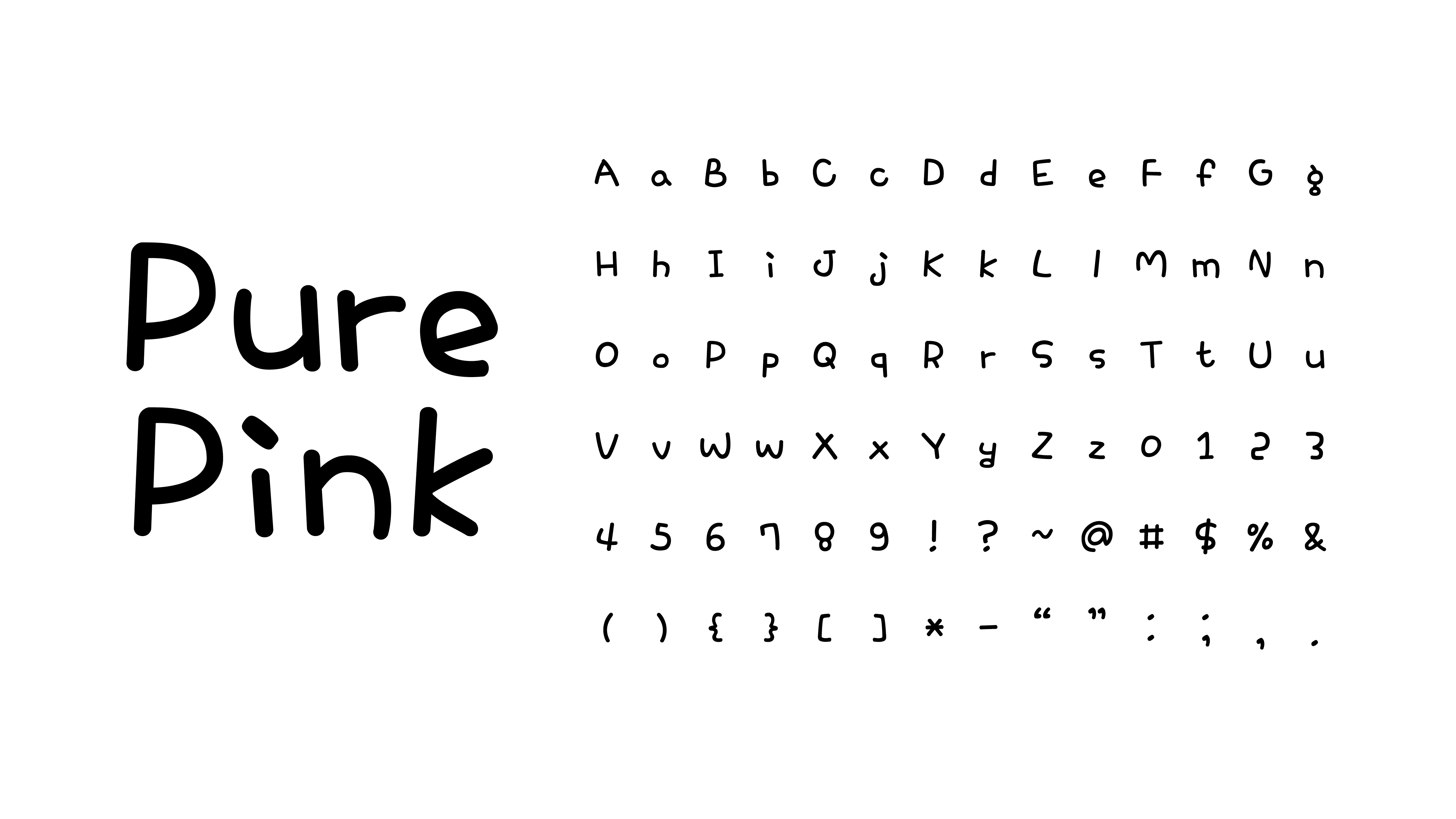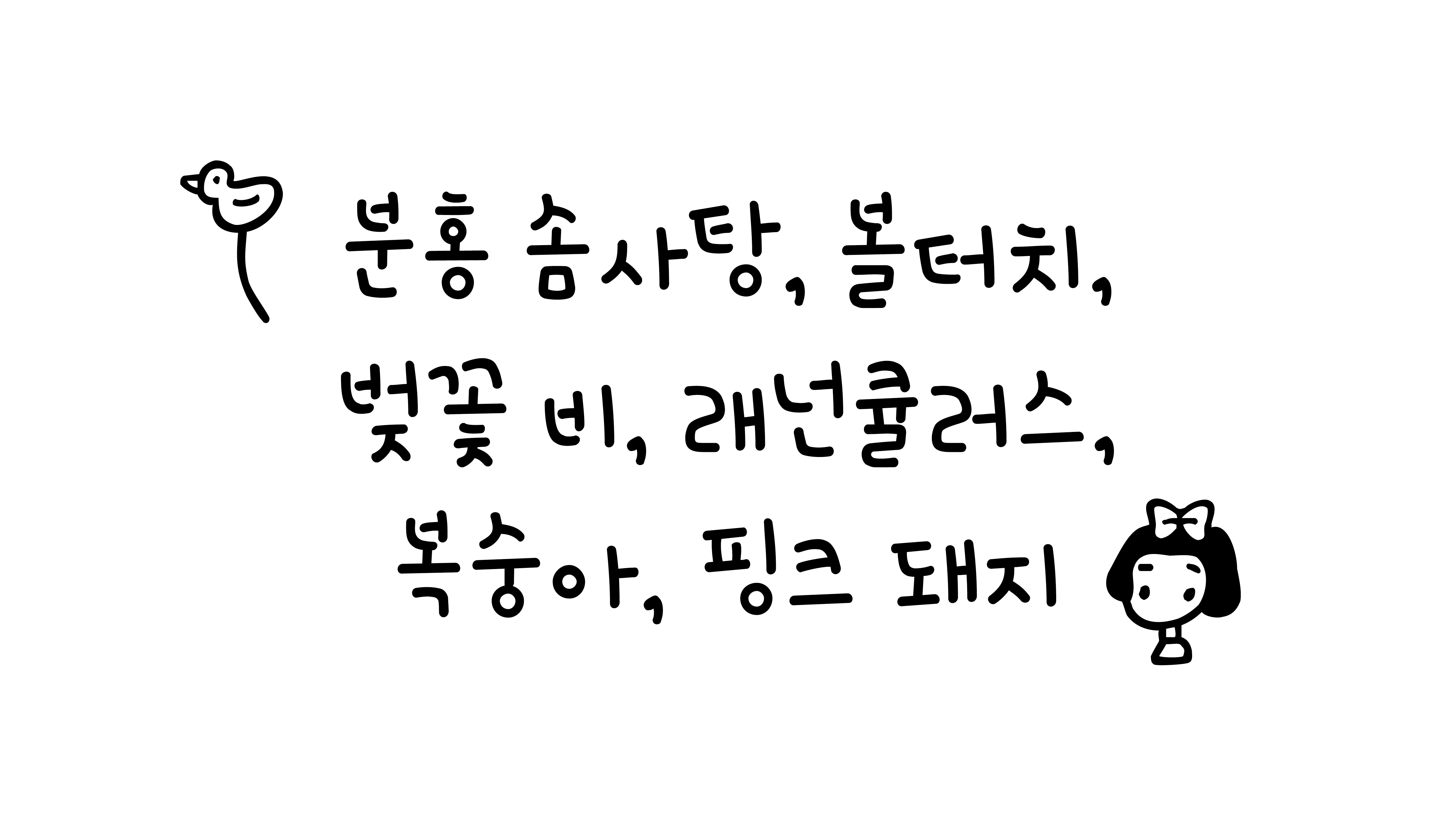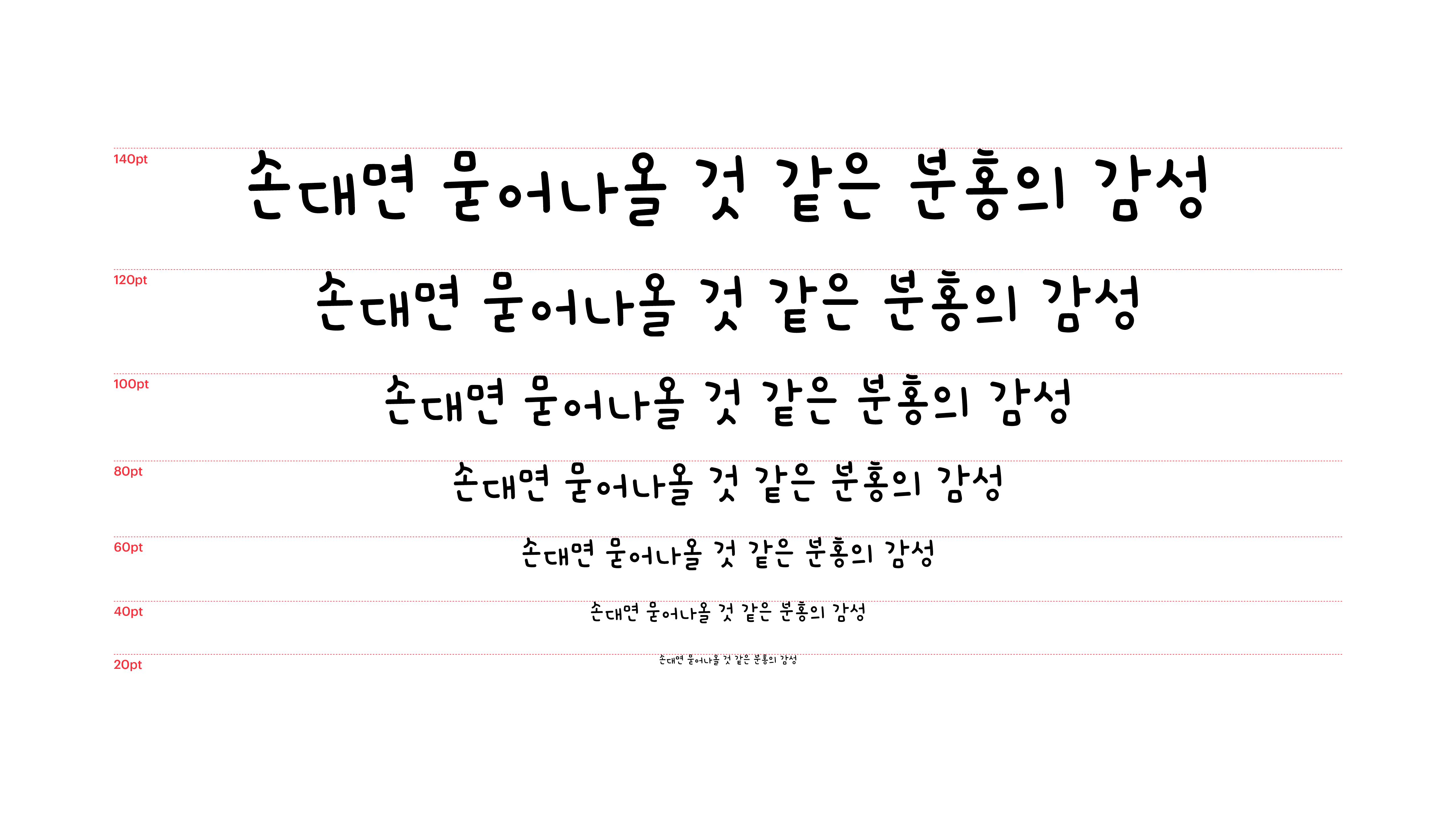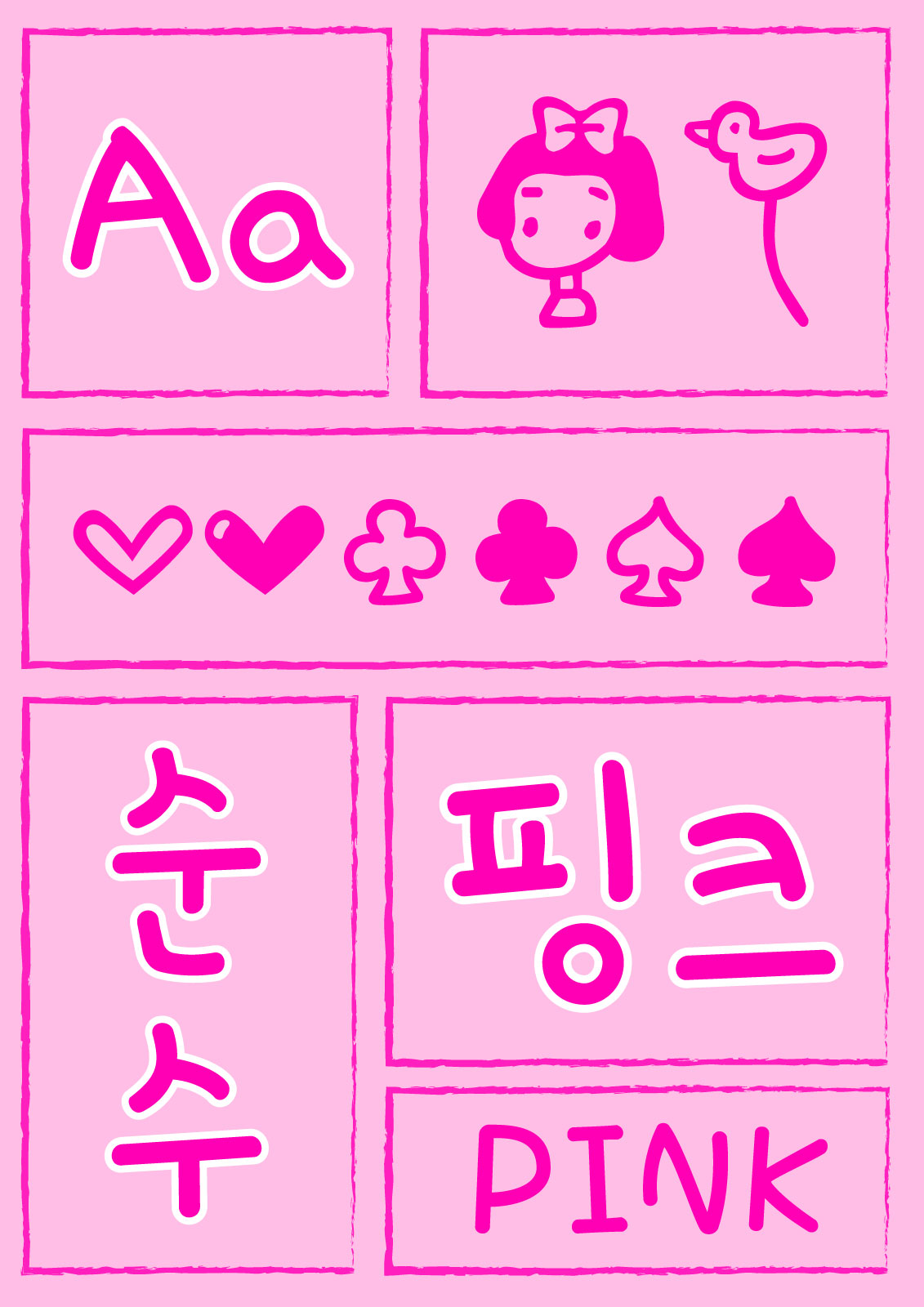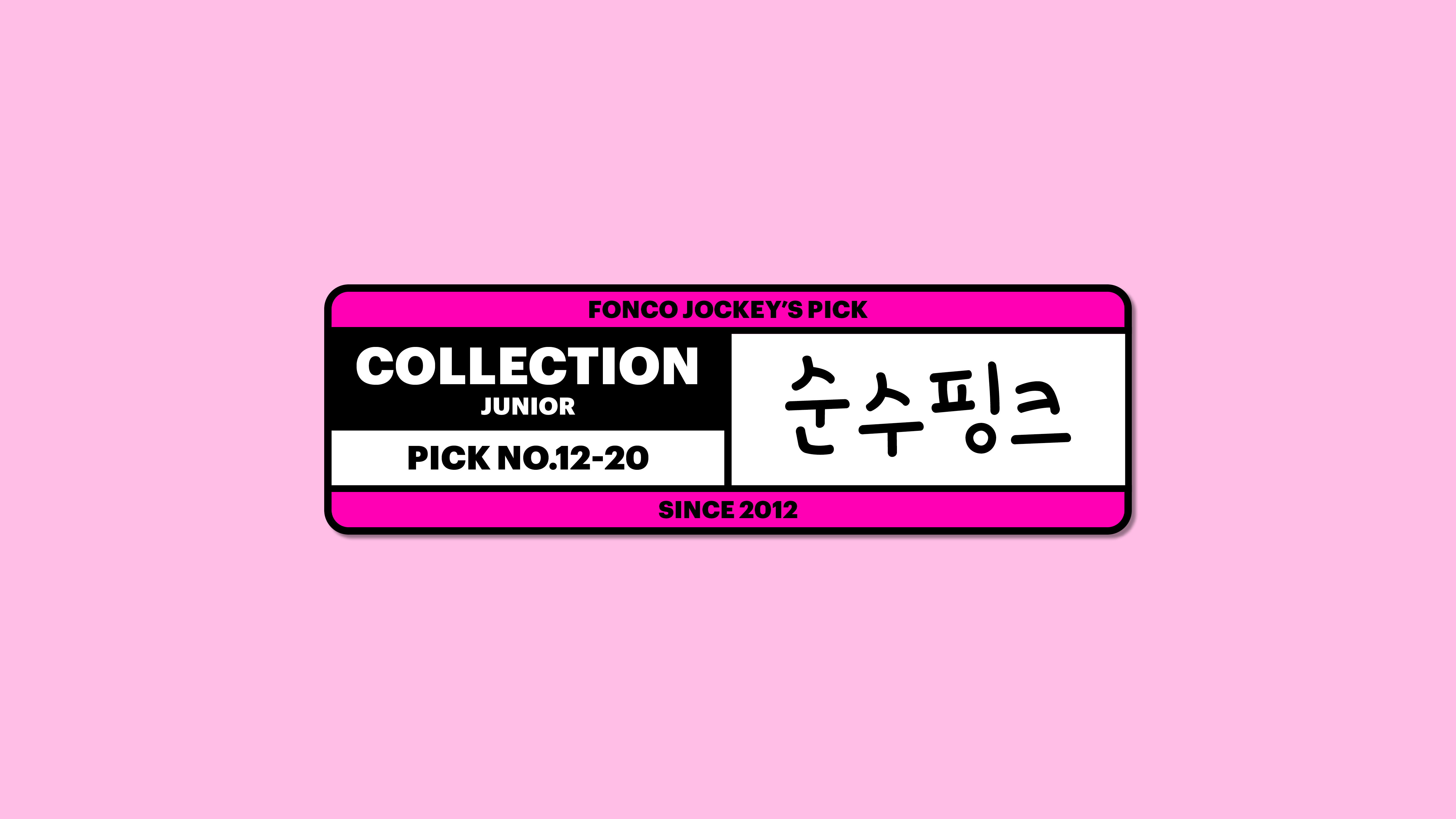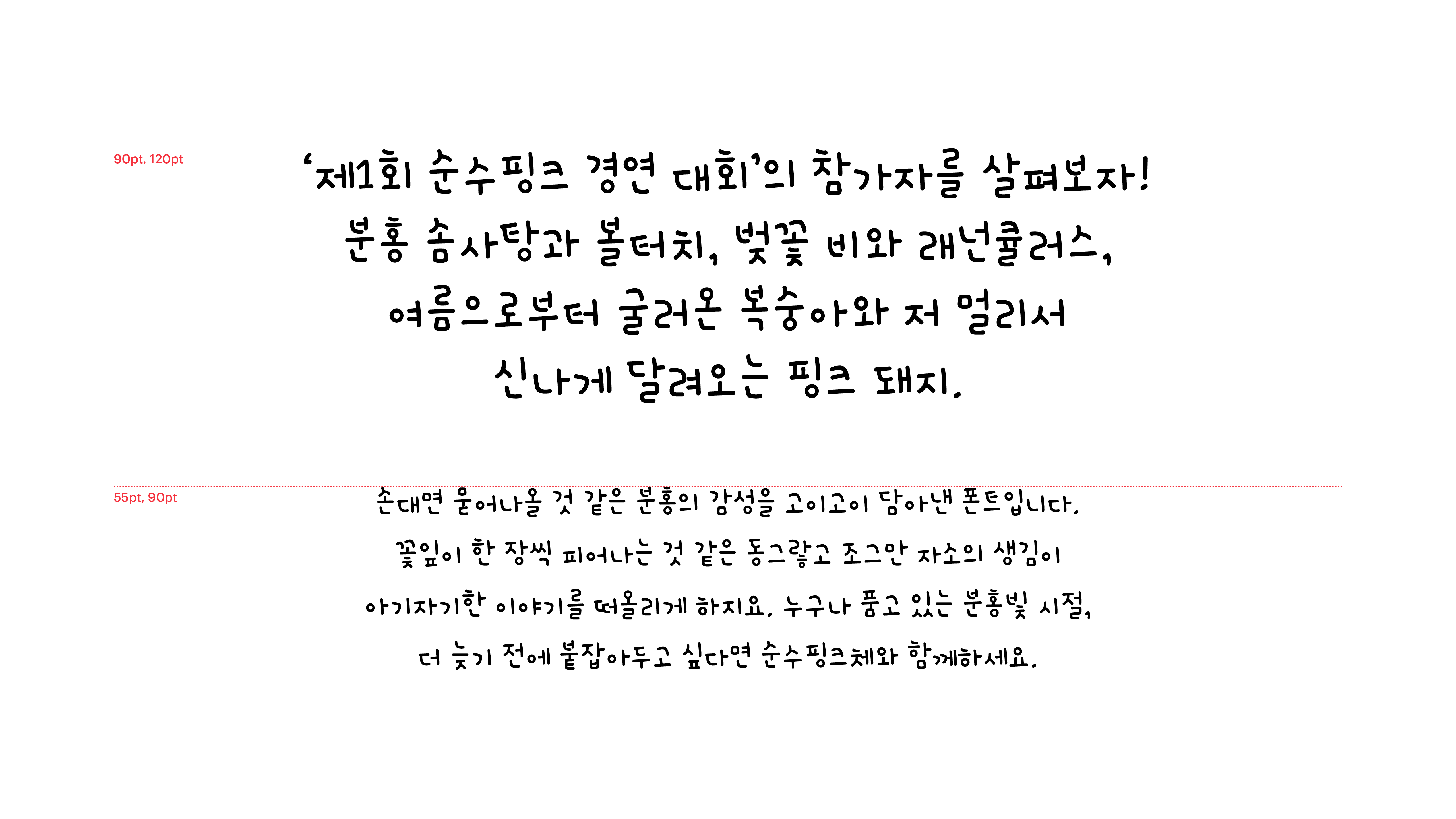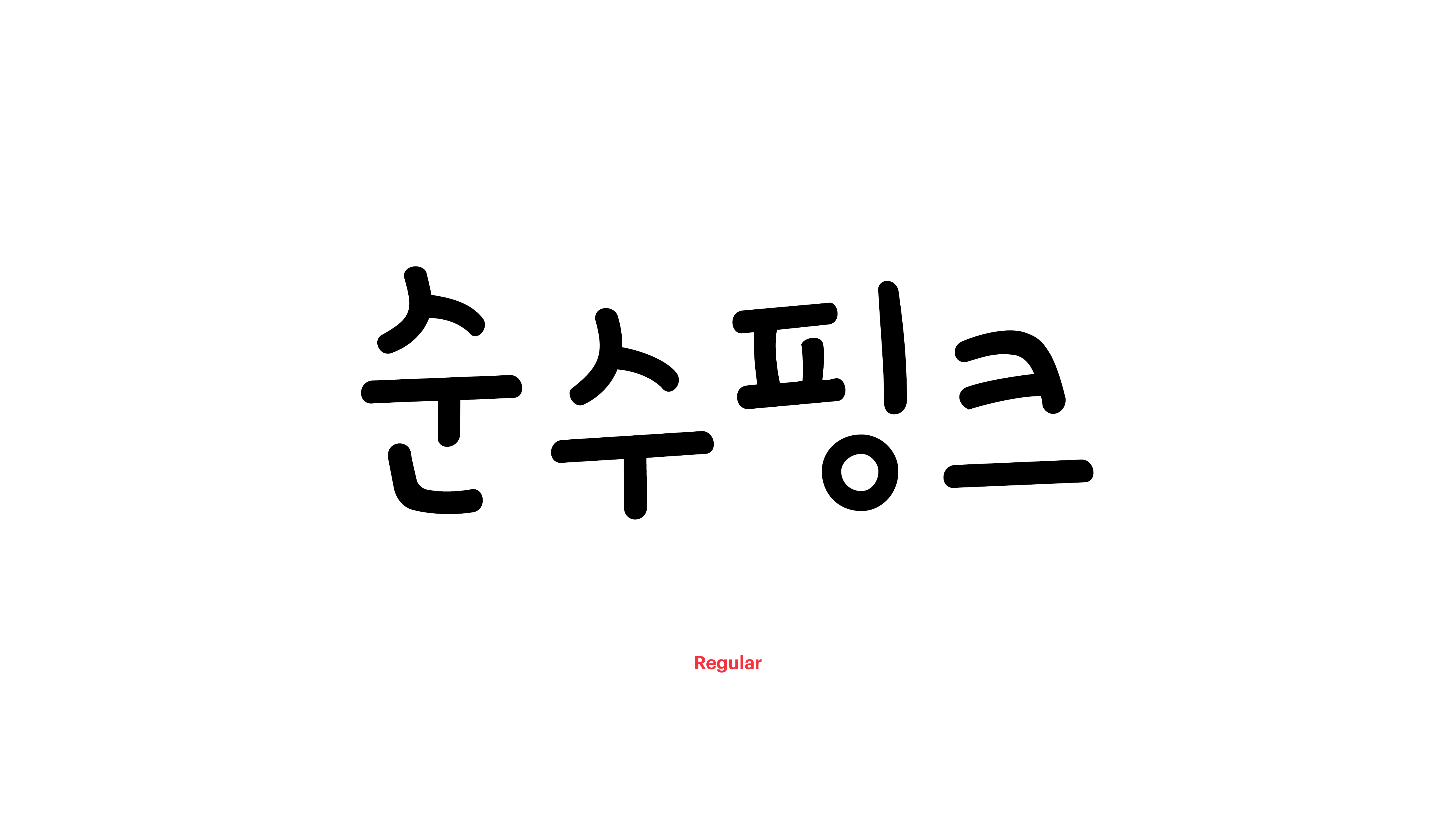
순수핑크
Yoon 순수핑크
손대면 묻어나올 것 같은 분홍의 감성을 고이고이 담아낸 폰트입니다. 꽃잎이 한 장씩 피어나는 것 같은 동그랗고 조그만 자소의 생김이 아기자기한 이야기를 떠올리게 하지요. 누구나 품고 있는 분홍빛 시절, 더 늦기 전에 붙잡아두고 싶다면 순수핑크체와 함께하세요.